艺术字体在日常生活中经常见到,不管是电视节目中、宣传海报上、还是网络交流中,大家都非常喜欢使用艺术字。虽然个人也会使用艺术字,但要说用艺术字用得最多的还是非设计师莫属,因为我们生活中见到的广告、海报都是设计师们设计出来的,因此艺术字对于设计师来说就显得至关重要,这关系到整个作品的协同、关系到作品表达出来的整体格调。下面就一起看看艺术字体设计的介绍。
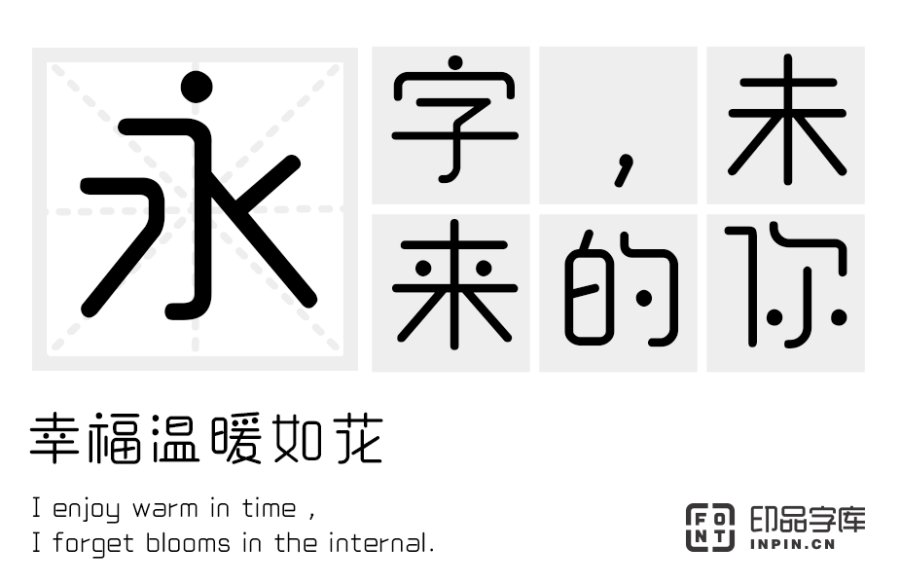
艺术字体主要指的是不同于我们平常书写的几种字体,它没有常用字体的那么有规矩,是设计师通过对常规字体进行变形,使字体达到某些独特的效果。艺术字具有美观有趣的特点,由于是汉字的独特变形,设计师们可以按照自己的喜好进行变形,使其更加美观。同时艺术字也可以带来更大的视觉冲击,比较醒目和张扬,更容易让人观察到。这种创新型的字体所具有的特点着实是设计师们的一个好帮手,能够让设计作品独具一格,受到更多关注。
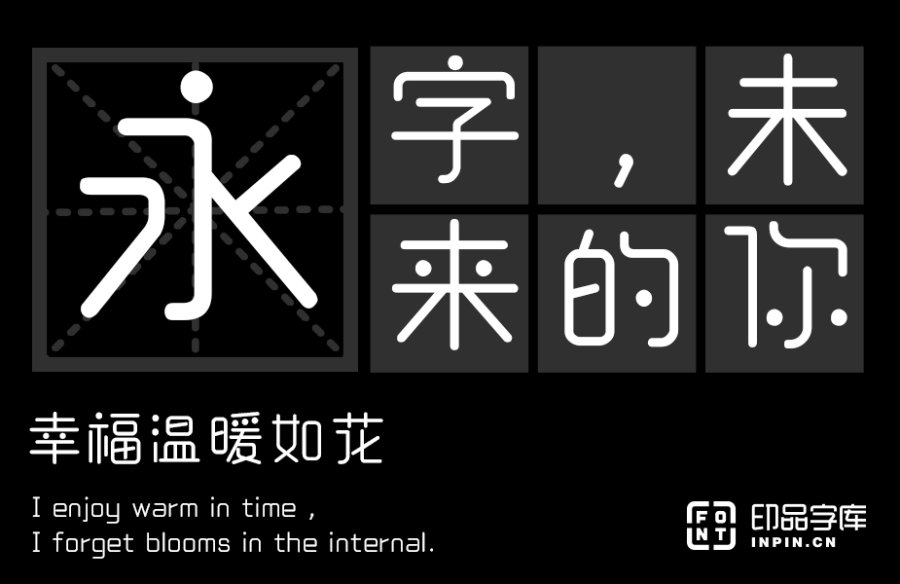
设计师为了设计作品的整体效果,在选择字体时往往会选择艺术字,但许多字体在设计软件中没有,这时设计师不得不自己设计艺术字,但设计艺术字往往要花费很长时间才能达到想要的效果,比较浪费时间也比较麻烦,容易致使工作效率不高。